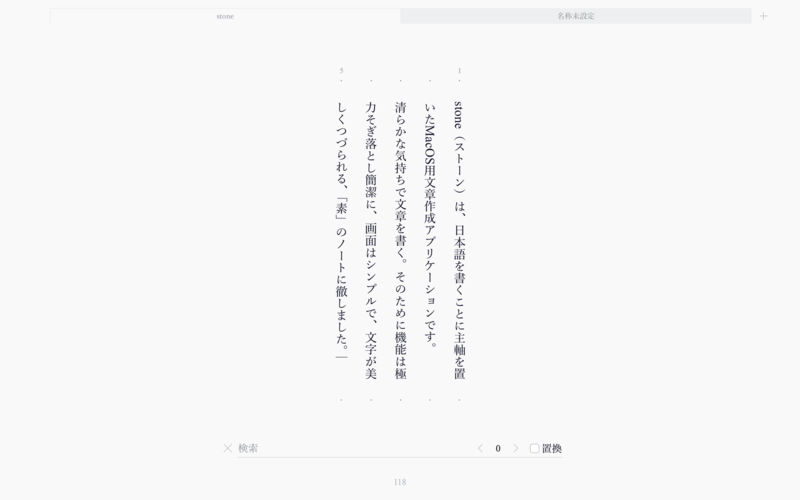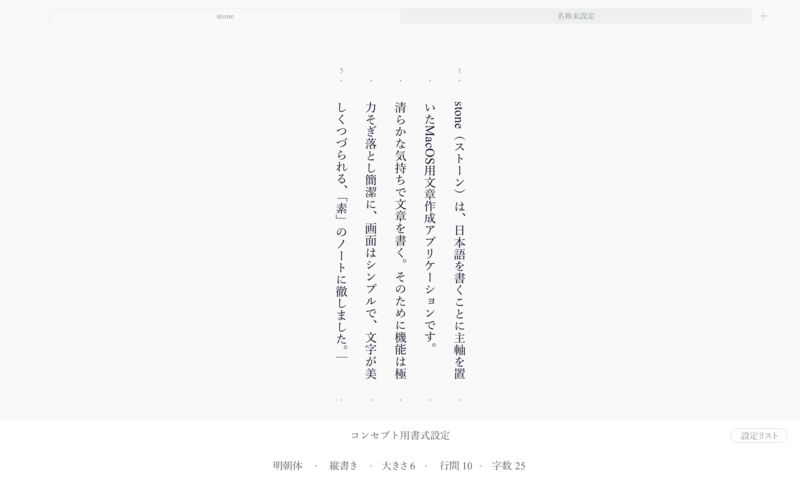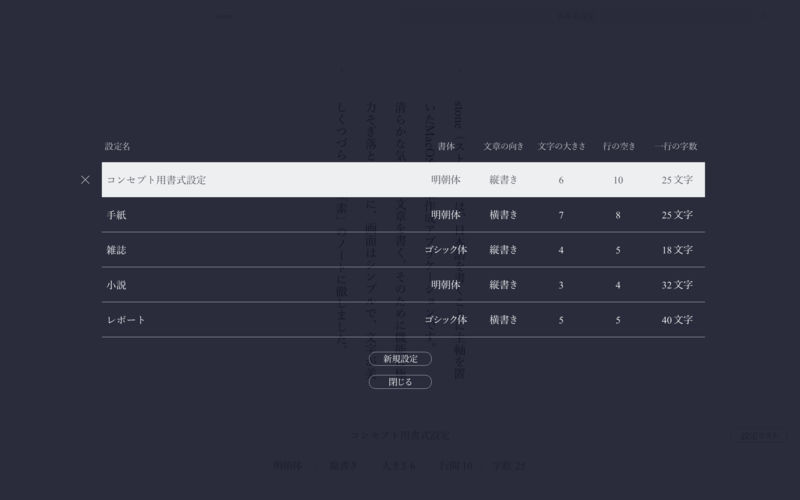
stone
株式会社日本デザインセンターからmacOS用の日本語向けテキストエディタアプリ「stone」を発売された。
「stone」は縦書きに対応した日本語向けテキストエディタ。必要な機能を最小限にとどめられたシンプルな画面に文字を美しく綴れるのが特徴。執筆に集中できるように視界が煩雑にならないような工夫がなされている。主な機能として明朝体・ゴシック体による縦書き・横書きに対応。文字サイズ、行間行長の変更、保存や印刷などが可能。公開レビューでのフィードバックをもとに自動保存機能なども搭載している。
stoneで使用できるフォント
和文と欧文のフォントを組み合わせた「混植」と呼ばれるグラフィックデザインのノウハウを取り入れられている。選択できる書体は明朝体とゴシック体。
明朝体は「游明朝」と「Times New Roman」、ゴシック体は「游ゴシック」と「Helvetica Neue」を組み合わせたフォントが使用できる。
游明朝
游明朝体は「時代小説が組めるような明朝体」をキーワードに、単行本や文庫などで小説を組むことを目的に開発されており、字の大きさの揃った現代的な明るい漢字と、伝統的な字形を生かしたスタンダードな仮名の組み合わせは、これまでの明朝体とは違う特徴になっている。
游ゴシック
游ゴシック体は、游明朝体と一緒に使うことを想定して開発されたスタンダードな角ゴシック体。ややフトコロがせまい漢字と、伝統的なスタイルを持ったすこし小さな仮名の組み合わせが特徴。